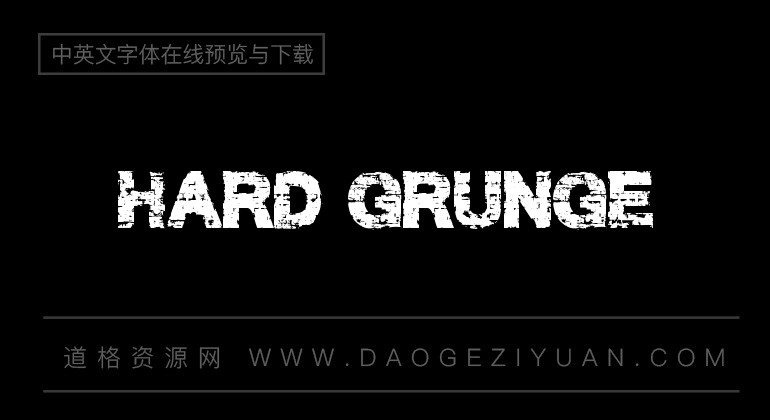
Hard Grunge
Hard Grunge 是一种具有粗糙、破旧、颓废感觉的字体风格。它通常用于表达摇滚、朋克、金属等音乐风格,以及相关的艺术或设计项目,如海报、标志、T恤等。 这种字体风格的特征在于,它的字母形状不规则、不对称,看起来像是手写的或者是从砖墙、铁皮上刻出来的。字母的边缘通常有锯齿和颗粒感,仿佛经历了岁月的洗礼和风雨的侵蚀。 Hard Grunge 字体的设计师们通常会用深色和金属色彩来搭配,营造出一种沉重、阴暗的氛围。这种字体风格的使用已经成为了流行文化中的一部分,它代表着年轻人对于反叛、自由和不羁的态度。
Hard Grunge是一款非常不错的手写艺术字体,具有很好的视觉感,适合于文化类的宣传设计、商业类品牌的广告和产品包装设计以及个性化文字排版等较多场景。